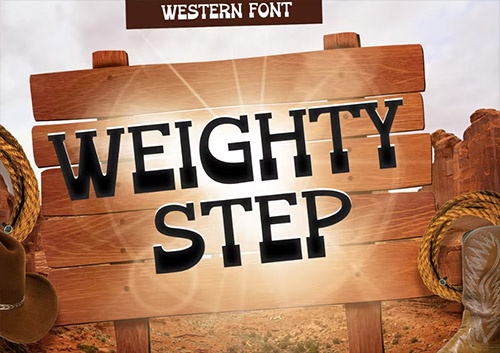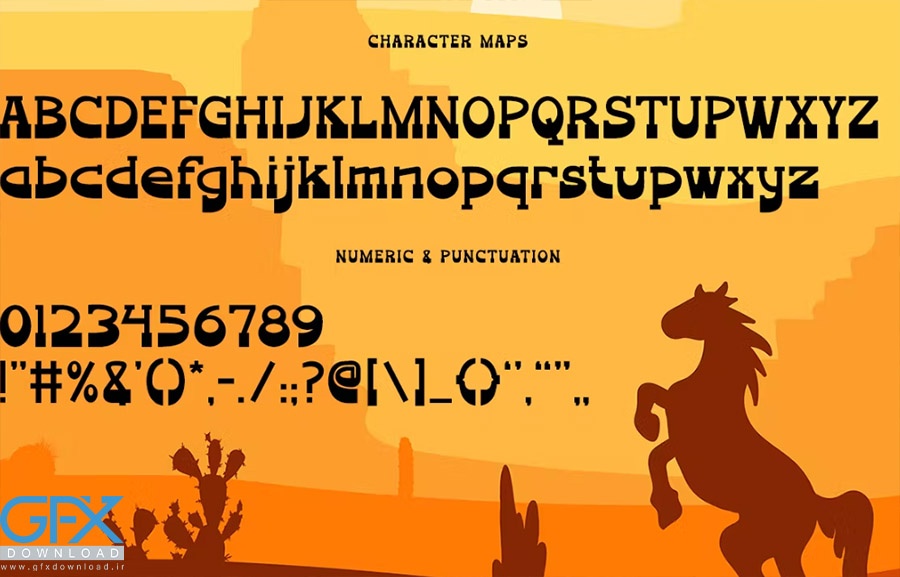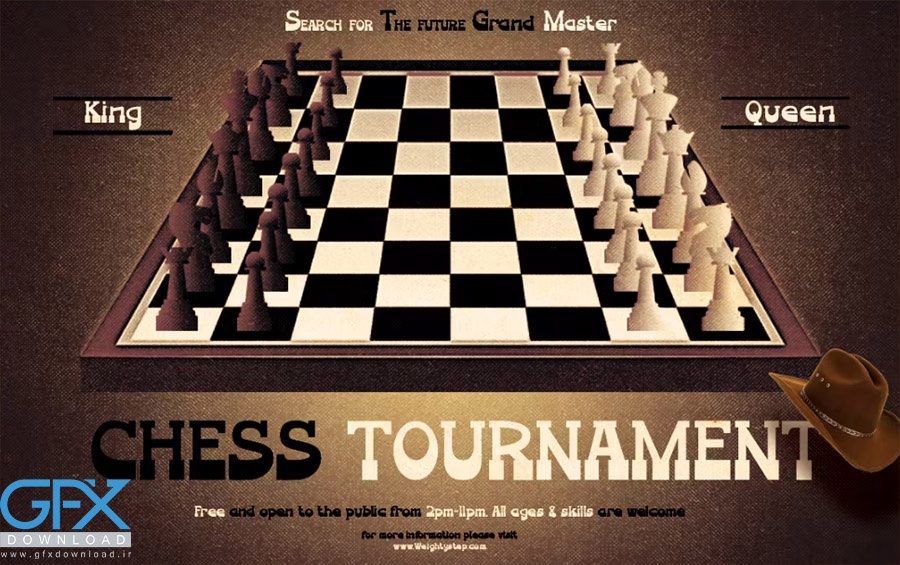
فونت وسترن کودکانه Weighty Step
دانلود فونت انگلیسی وسترن تم کودکانه Weighty Step
همانطور که در تصویر پیش نمایش مشاهده می کنید این فونت ، کلاه کابوی، خار و کمند. بیابان و ناهمواری دنیای وحشی را به ارمغان خواهد آورد. فونت وسترن کودکانه Weighty Step برای کارتون ها، برای بازی‌های تم وسترن ، پوسترهای رویداد کابوی، جلدهای یوتیوب، تصاویر کوچک یوتیوب، جلدهای صفحه رسانه‌های اجتماعی و غیره کاملاً مناسب است.
فونت وسترن انگلیسی Weighty Step